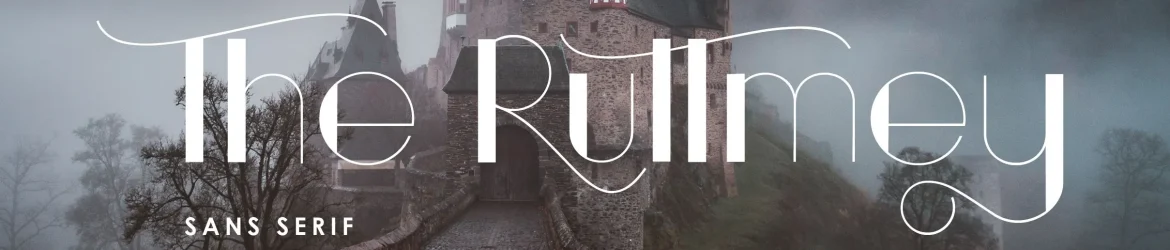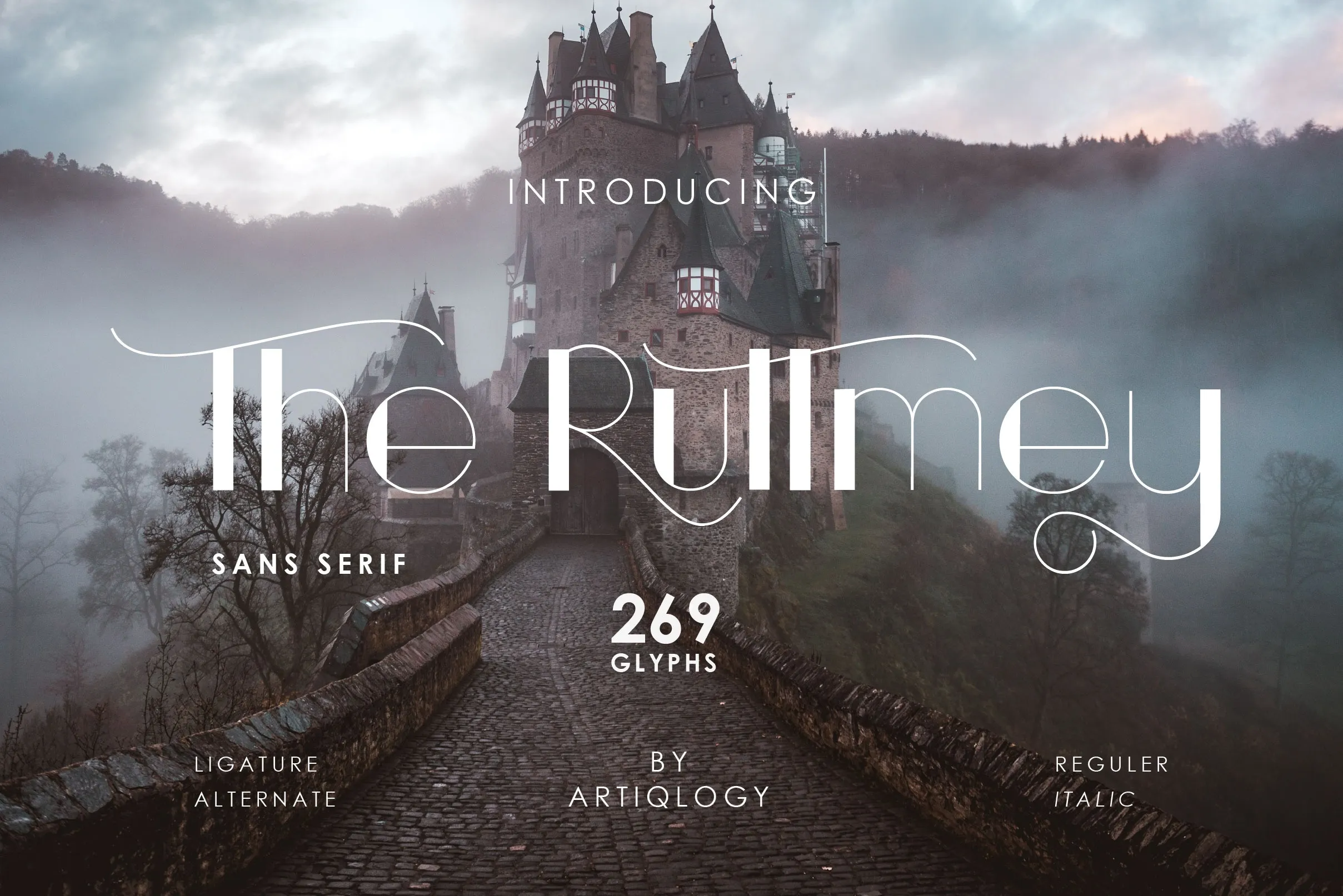
The Ruttmey Font – Fonte Grátis
The Ruttmey Font
A fonte “The Ruttmey Font” é uma elegante tipografia sans-serif que apresenta linhas suaves e curvas românticas, dando ao texto um ar atraente e moderno. Desenvolvida pela Artiqlogy, esta fonte tem um desenho limpo e belo dos caracteres, o que lhe confere uma aparência elegante para qualquer design formal ou informal. Suas linhas retas e curvas arredondadas criam um contraste interessante que faz deste fonte uma excelente escolha tanto para textos formais quanto não-formais. Em cada página de seu site ou em sua próxima publicação, ela pode transformar o texto sem ser intrusiva, fornecendo a perfeita mistura de elegância e modernidade que você precisa. Seja você um designer de gráficos profissional ou uma editora digital, “The Ruttmey Font” é uma excelente adição à sua coleção de fontes.